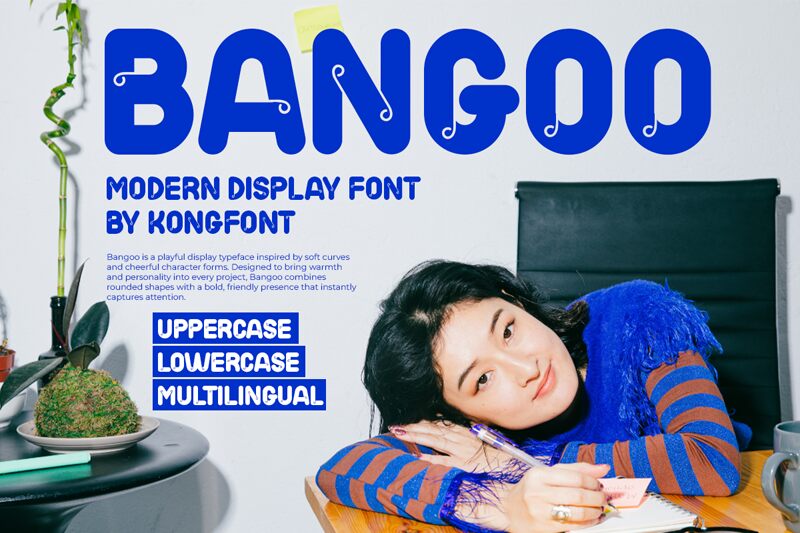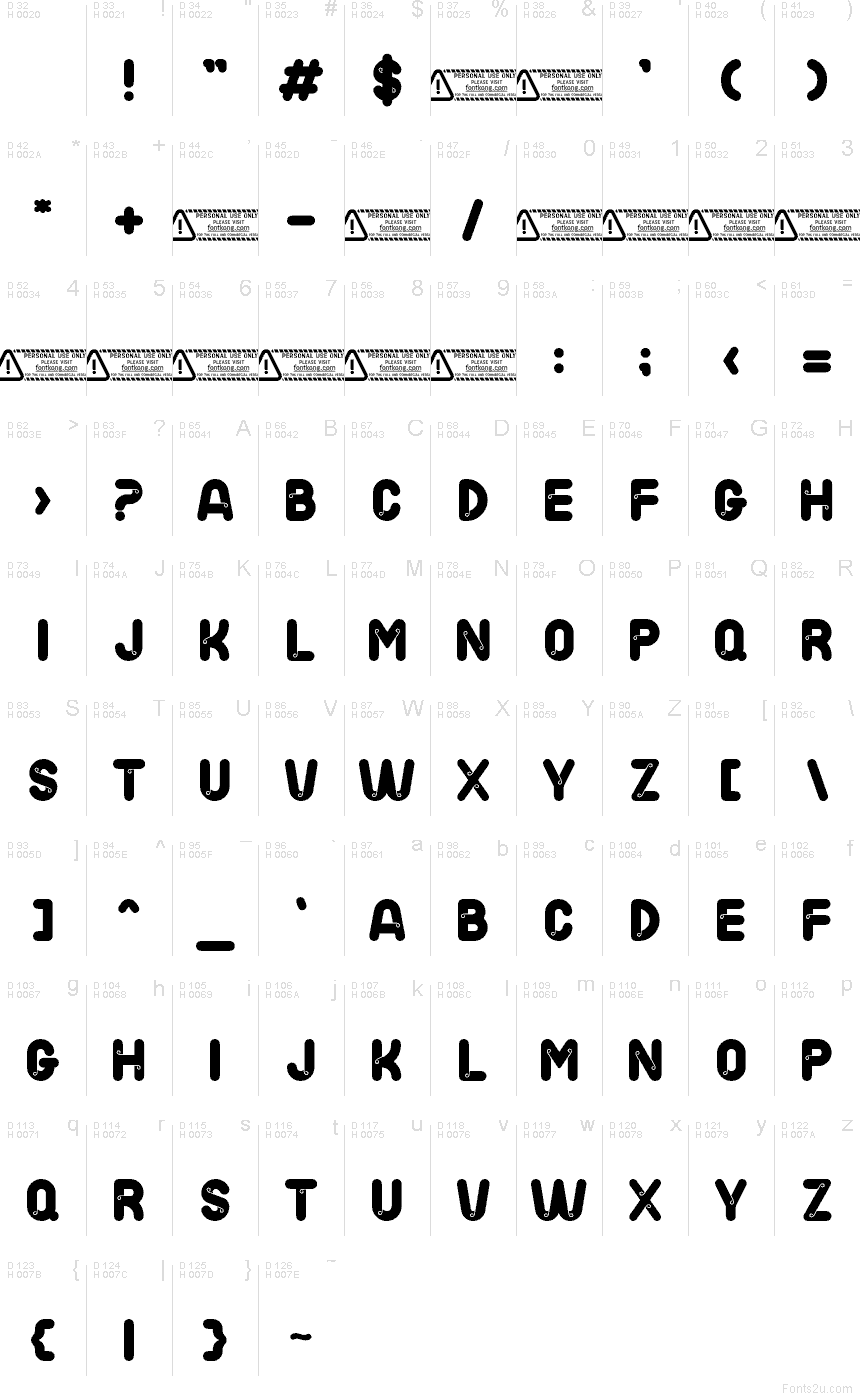
Bangoo od Kong Font to nowoczesny, darmowy krój pisma typu display, charakteryzujący się dużymi, zaokrąglonymi wielkimi literami i zabawnym, retro klimatem. Znaki są wyraziste i mają miękkie krawędzie, a każdy z nich wzbogacono o niewielkie, zakrzywione wycięcia przypominające liternictwo pop lat 60. Dzięki temu alfabet zyskuje graficzny, plakatowy rytm, unikając przy tym monotonii zwykłych bloków geometrycznych.
Ten darmowy font świetnie sprawdzi się na plakatach muzycznych, opakowaniach, w brandingu kawiarni, nagłówkach i na okładkach – wszędzie tam, gdzie urok jest ważniejszy niż powściągliwość. Pasuje również do monogramów i krótkich grafik w mediach społecznościowych, ponieważ wewnętrzne zakrzywienia sprawiają, że wielkie litery pozostają żywe nawet w krótkich tekstach.